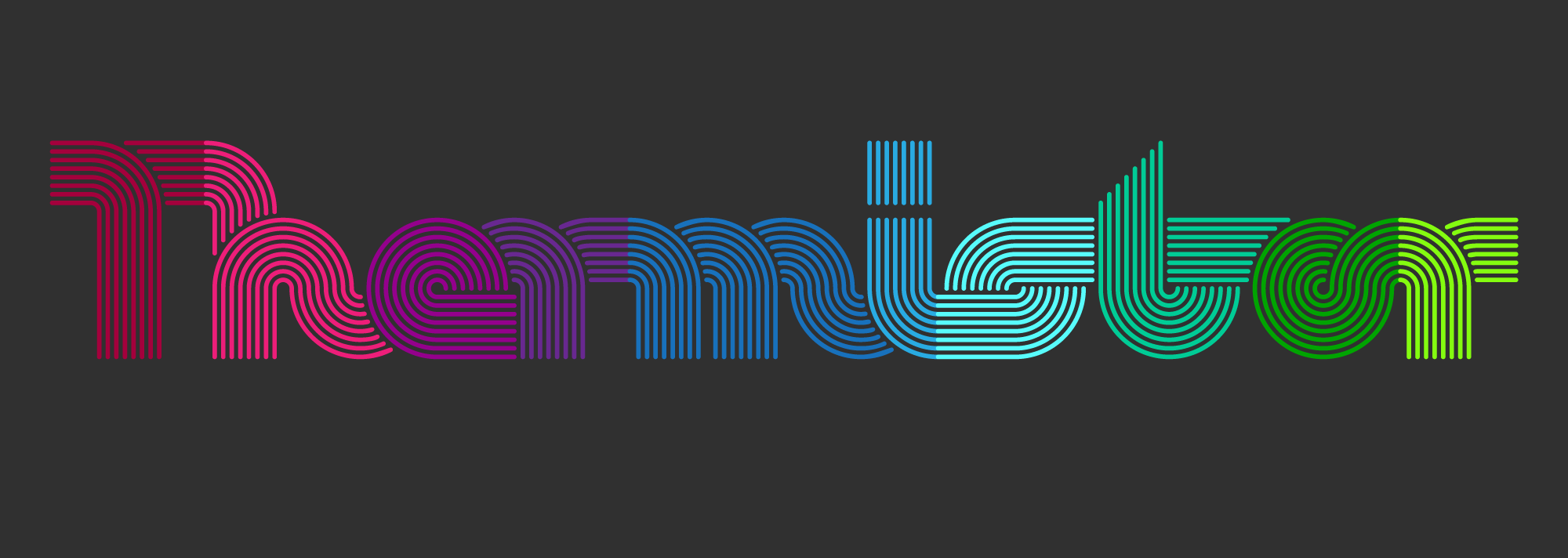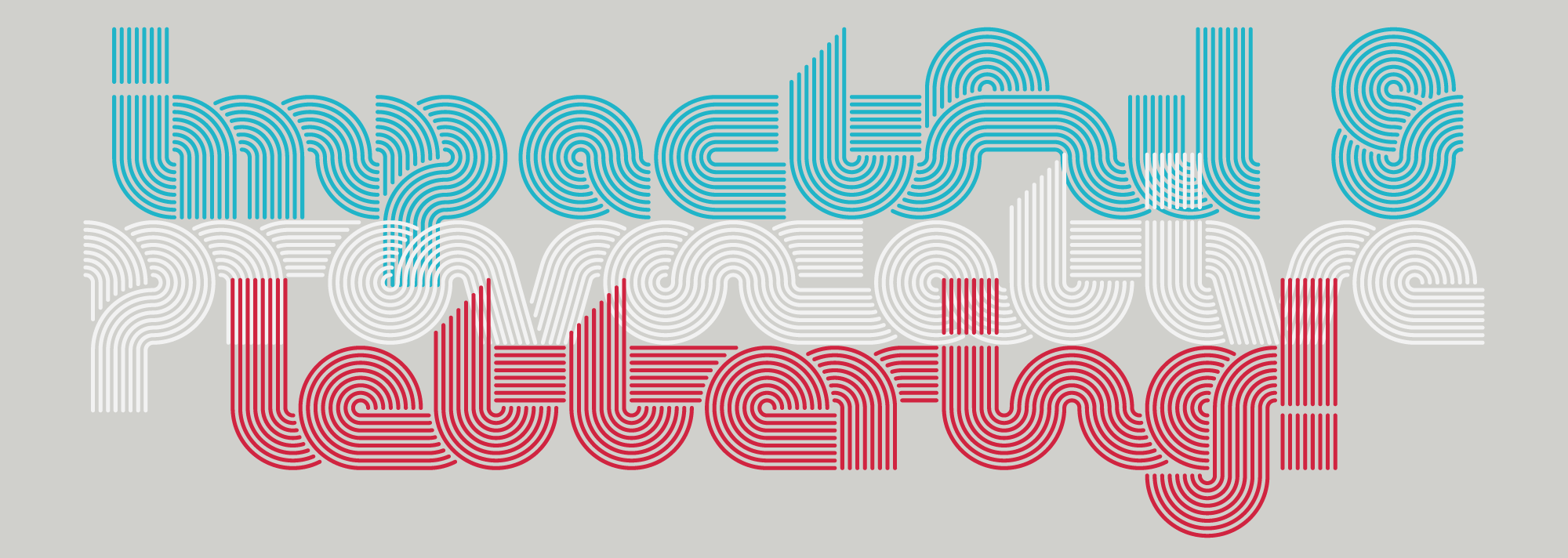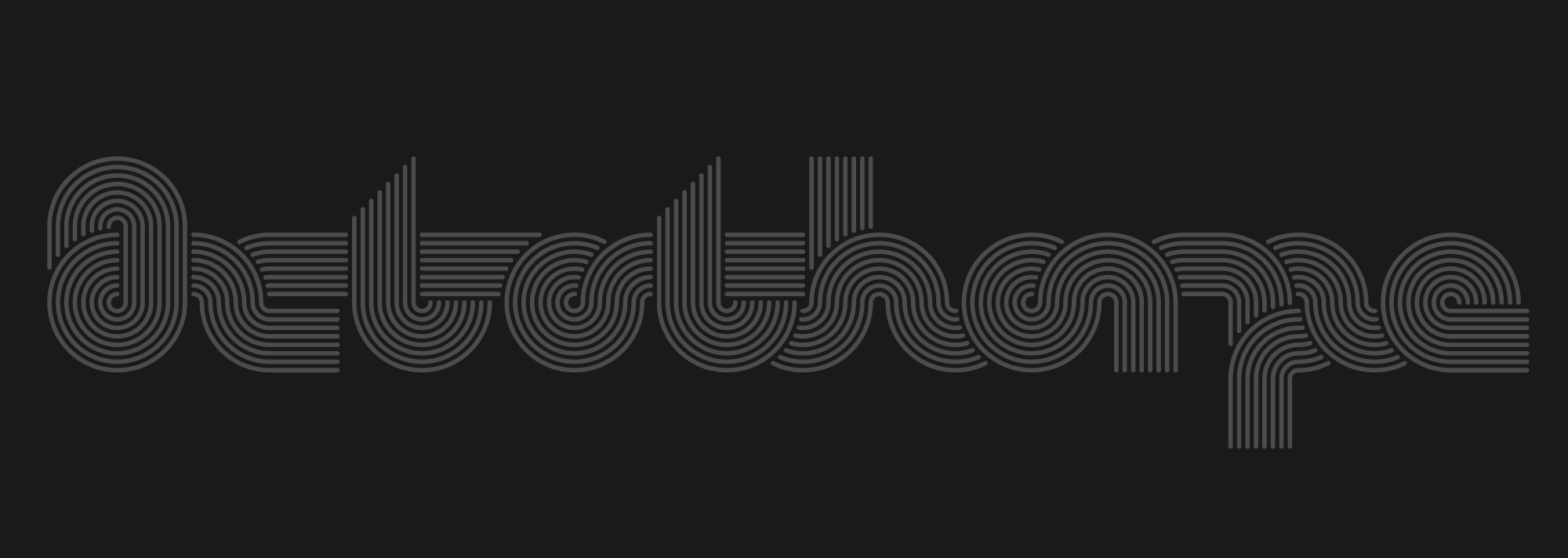
Die Octothorpe von Jorge Iván Moreno Majul basiert auf der Letraset-Schrift Stripes aus den 1970er-Jahren. Mit dieser Schrift konnten Gestalter interessante Schriftbänder erzeugen, auch über Schriftzeilen hinweg. Die Octothorpe bringt das Design mit einem großen Zeichenvorrat ins 21. Jahrhundert. Die Schrift verfügt über eine erweiterte lateinische Belegung sowie griechische und kyrillische Zeichen, verbundene und unverbundene Formen, mehrere Ziffernsets, Ligaturen und Pfeile.